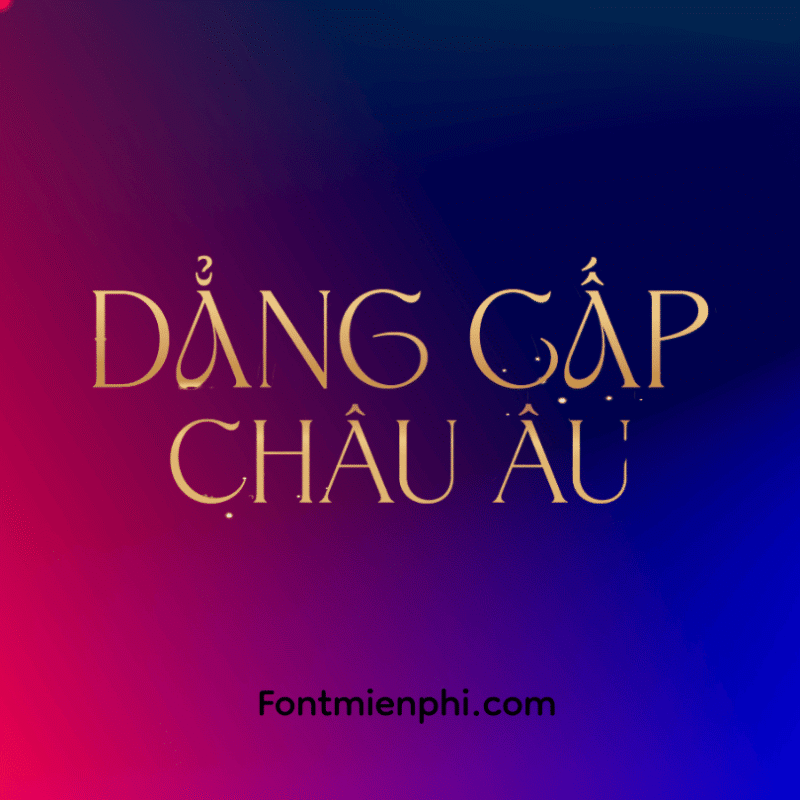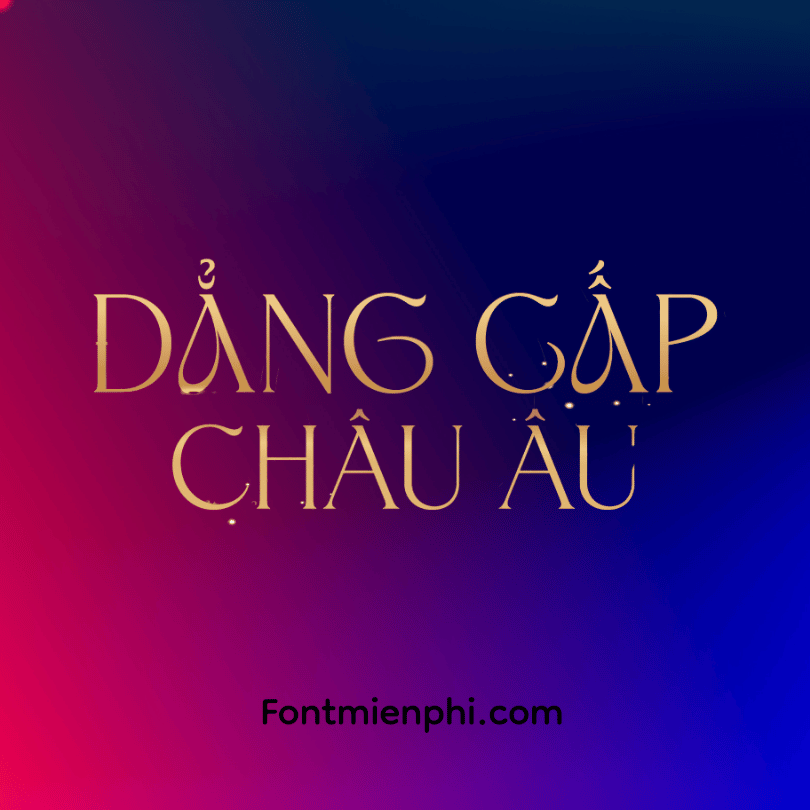
Font Việt hóa 1FTV VIP Calabassas
Font Việt Hóa 1FTV VIP Calabassas – Phong Cách Hollywood Sang Chảnh
Đặc điểm nổi bật:
• Phong cách retro modern lấy cảm hứng từ biển tên Beverly Hills
• Nét chữ thanh mảnh pha chút cổ điển, cực Tây
Ứng dụng đắt giá:
Thiết kế logo thương hiệu thời trang cao cấp
Billboard quảng cáo sản phẩm luxury
Tạp chí thời trang, ấn phẩm sang trọng
Bao bì mỹ phẩm, nước hoa đẳng cấp
Background phim ảnh, MV ca nhạc
Tips sử dụng xịn xò:
✓ Kết hợp với tone màu gold sang trọng
✓ Dùng làm font chính cho các thương hiệu hướng tới giới thượng lưu